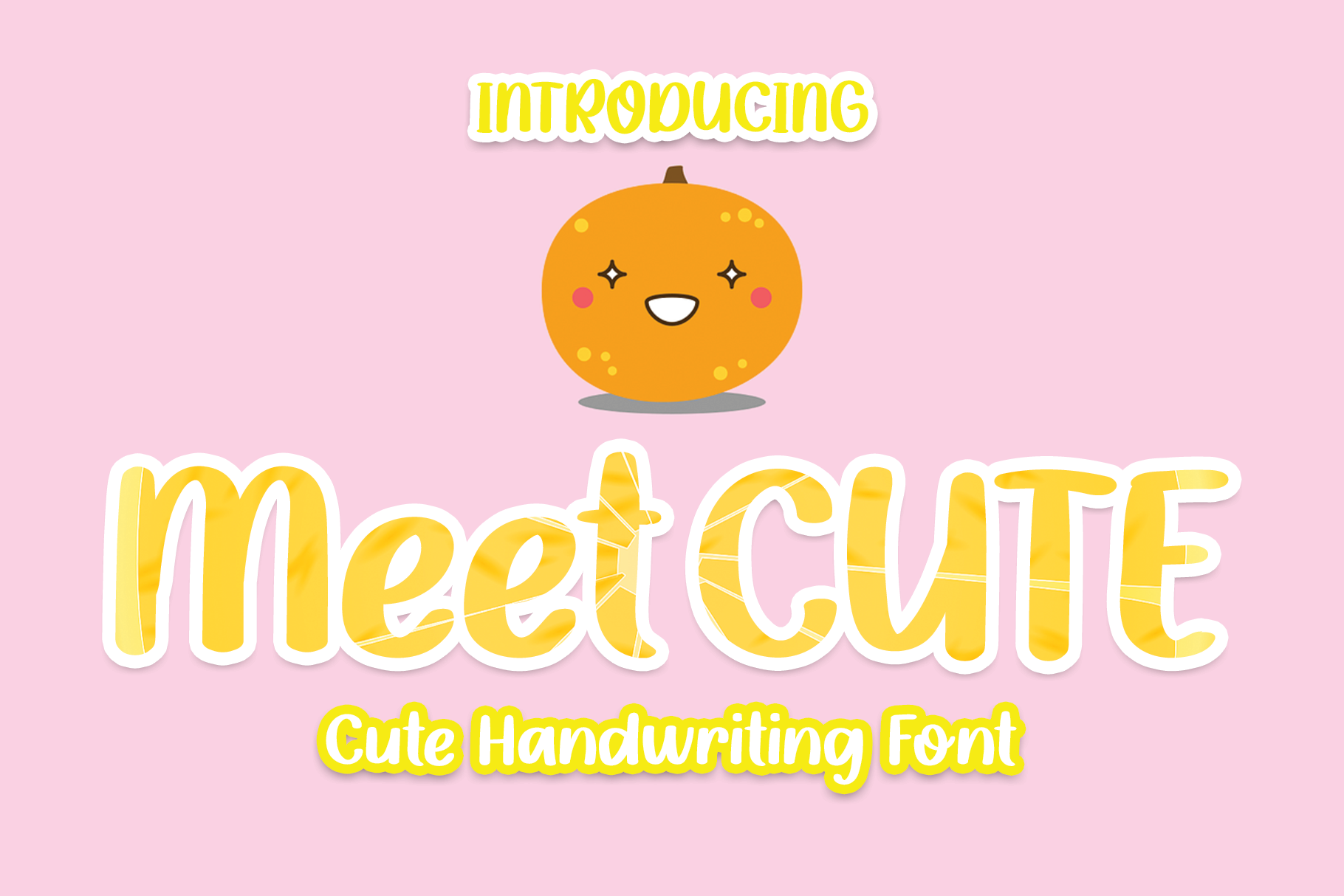
Meet Cute Font – Fonte Grátis
Meet Cute Font
A fonte Meet Cute é uma opção para qualquer designer gráfico que procura um estilo alegre e descontraído. Ela se destaca entre outras fonts com sua aparência suavemente pintada, repleta de personalidade escrita à mão. Este tipo de font oferece uma gama incrível de usos possíveis – seja você criando gráficos de redes sociais, infográficos ou design editorial. Sua simplicidade e habilidade para capturar o espírito do momento a tornam um excelente recurso no seu arsenal de fonts. Com este tipo, qualquer projeto ganha uma personalidade única. Ela também é uma ótima escolha para aqueles que valorizam uma fonte com uma aparência autêntica e descontraída. O designer el hotcig criou essa font para quem busca um toque acolhedor em suas criações, seja ela parte de uma campanha publicitária ou uma linha editorial pessoal.
Designer: el hotcig